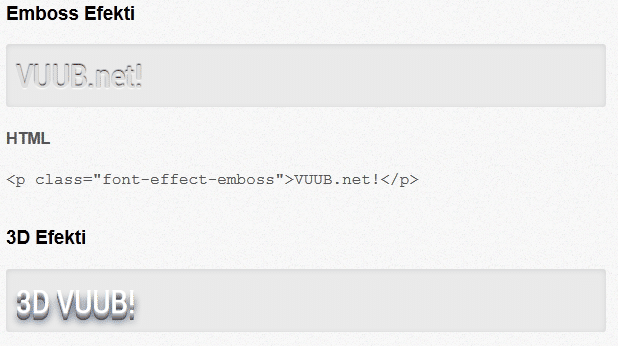
Google Web Font Efektleri
Google'ın ücretsiz olarak sunduğu web yazı tipleri aracılığı ile birbirindne güzel efektleri basitçe uygulayacağız ve örnekleyeceğiz.
CSS3 kullanılmaya başlandığından bu yana sade yazı tipleri yerine sadece css düzenlemesi yaparak yazı tipine çeşitli stiller ekleyebiliyoruz. Google'ın ücretsiz olarak sunduğu web yazı tipleri aracılığı ile bunu nasıl yapabileceğimize göz atacağız. Google Web Font - Çarpıcı Efektler Google tarafından gelen güzel bir açıklama sonucunda Google Web Fonts dahilindeki yazı tiplerine birbirinden farklı 25 yazı tipi efektini uygulamamız mümkün. Bunu gerçekleştirebilmek için basit bir ek kod uygulaması yapıyoruz, bu uygulamayı google tarafından bize verilen yazı tipi kodu üzerinde gerçekleştiriyoruz. Aşağıdaki örnek durumu daha net açıklayacaktır. Daha sonrasında basitçe efekti kullanacağımız alandaki class'a verdiğimiz ismi tanımlıyoruz.
Bu efekti nasıl oluşturduğunuzu merak ederseniz aşağıdaki kodu inceleyebilirsiniz.
.font-effect-shadow-multiple {
text-shadow: .04em .04em 0 #fff,.08em .08em 0 #aaa;
-webkit-text-shadow: .04em .04em 0 #fff, .08em .08em 0 #aaa;
}
Google Web Font - Çoklu Efekt Uygulaması
Birden fazla efekt hazırlayabilmemiz mümkün, bu efektleri sayacak olursak; Multiple Shadow, Emboss ve 3D. Aşağıdaki örnekte olduğu gibi kullanıldığında sorunsuzca çalışmakta.Ortaya çıkan sonuç şu şekilde oluşmakta;